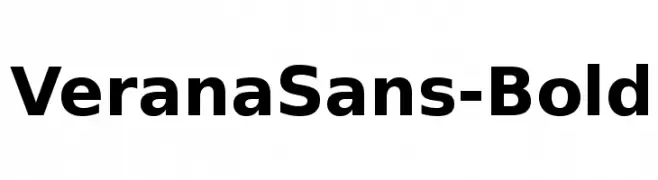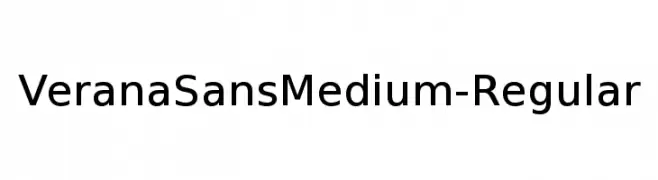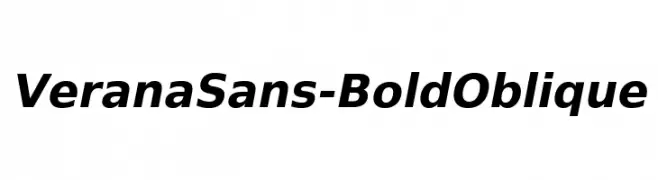
( Fonts by Arkandis Digital Foundry )
A modern, geometric font with a clean, monospaced appearance and subtle rounded edges.
( Fonts by Arkandis Digital Foundry )
A modern, geometric font with uniform stroke widths and a monospaced appearance.
( Fonts by Arkandis Digital Foundry )
A modern, semi-bold oblique typeface with a sleek, condensed style.
( Fonts by Arkandis Digital Foundry )
A bold, modern sans-serif font with strong, uniform strokes and excellent readability.
( Fonts by Arkandis Digital Foundry )
A bold, modern sans-serif font with clean, robust letterforms.
( Fonts by Arkandis Digital Foundry )
A modern, oblique sans-serif font with clean lines and a dynamic appearance.
( Fonts by Arkandis Digital Foundry )
A modern, clean sans-serif typeface with balanced proportions and uniform stroke width.
( Fonts by Arkandis Digital Foundry )
A modern, oblique sans-serif font with balanced proportions and clean lines.
( Fonts by Arkandis Digital Foundry )
A modern, oblique sans-serif font with clean lines and a dynamic slant.
( Fonts by Arkandis Digital Foundry )
A bold, oblique sans-serif font with a modern and dynamic style.
近期热门包括 ElectrumADFExp-Regular, ElectrumADFExp-Light, ElectrumADFExp-SemiBoldOblique, VeranaSans-Bold and VeranaSansDemi-Regular 它们在清晰度与个性之间取得平衡,适用于科技品牌、编辑排版与社媒视觉。